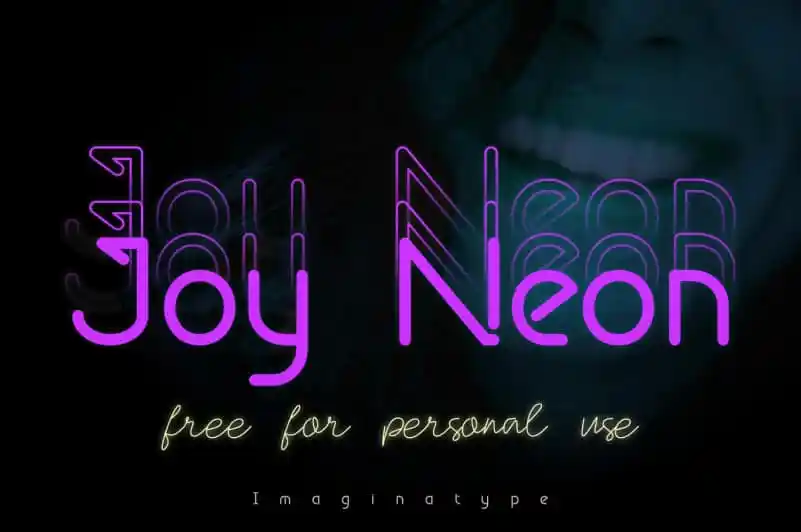
A Joy Neon Font é uma fonte sans-serif inspirada no design neon de um café noturno, revigorando a atmosfera vibrante e vibrante dessas lojas com sua textura complexa. Esta fonte não apenas oferece um toque autêntico aos seus projetos gráficos, mas também oferece uma gama incrivelmente diversificada que pode se adaptar facilmente a diversos estilos de design. Desenvolvida pelo designer Nuryanto Dwi, ela é perfeita para adicionar um toque único e contemporâneo ao seu trabalho. A sua estrutura fluida e detalhes distintos garantem que seja uma escolha ótima tanto para projetos digitais quanto impressos. Engrenagem-se nessa experiência visual vibrante da Joy Neon Font, elevará os seus trabalhos gráficos para um novo nível de impacto.
Designer: Nuryanto Dwi